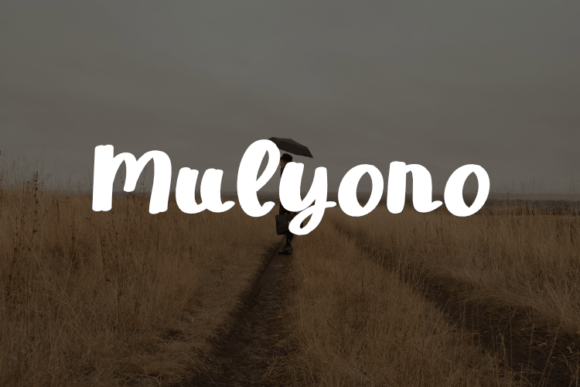
Mulyono
Nếu bạn đang tìm kiếm các tài nguyên chất lượng cao như Mulyono, gói cao cấp này là một lựa chọn tuyệt vời cho các dự án sáng tạo của bạn.
Được chế tác với độ chính xác cao, Mulyono cung cấp các vector sạch, kiểu chữ mượt mà và giấy phép thương mại để bạn yên tâm.
Cho dù bạn đang tạo sản phẩm POD (In theo yêu cầu), thiệp mời đám cưới hay đồ họa mạng xã hội, Mulyono đều là một sự lựa chọn lý tưởng.